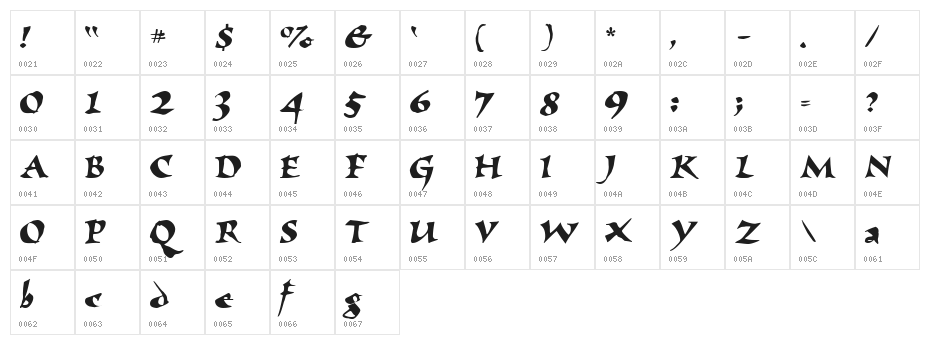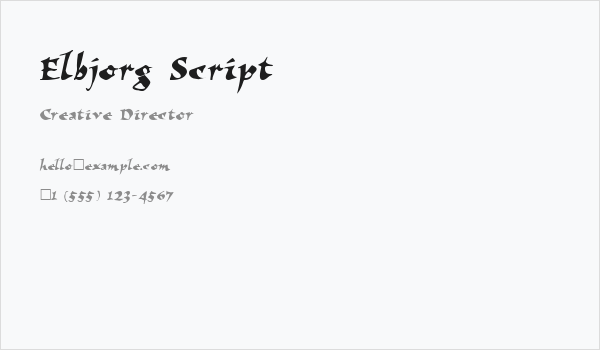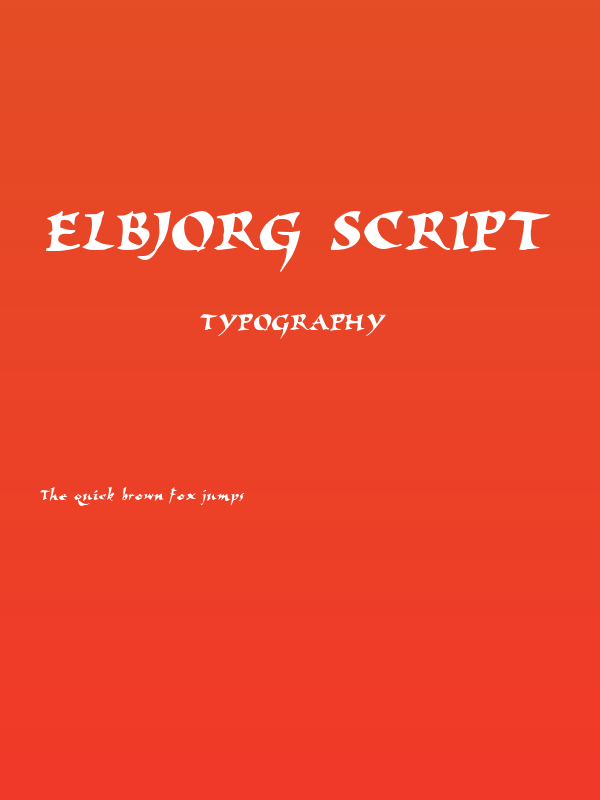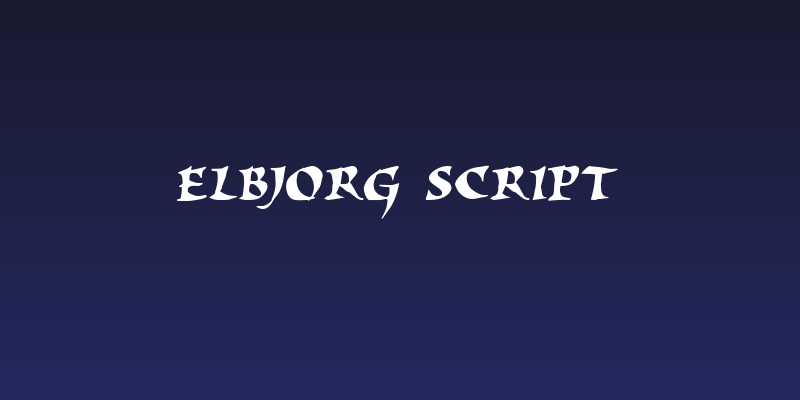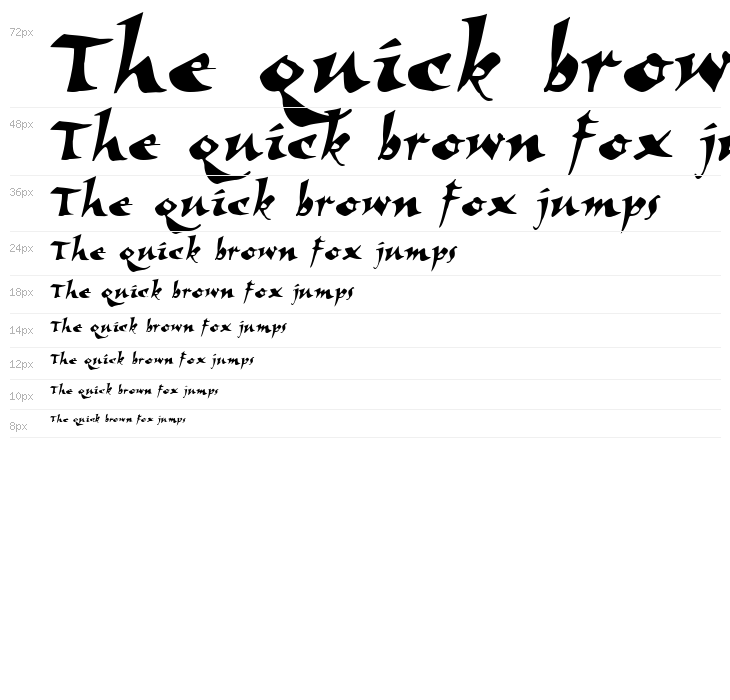
Elbjorg Script Font
| Anwendungsfall | Logos, Headlines, Invitations |
| Vorgeschlagene Projekte | Ideal for historical-themed designs, book covers, invitations, and branding that requires a dramatic and elegant touch. |